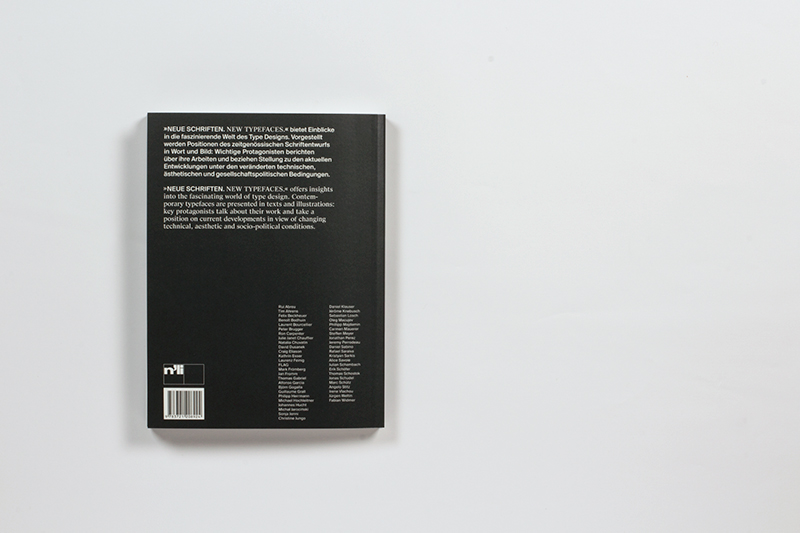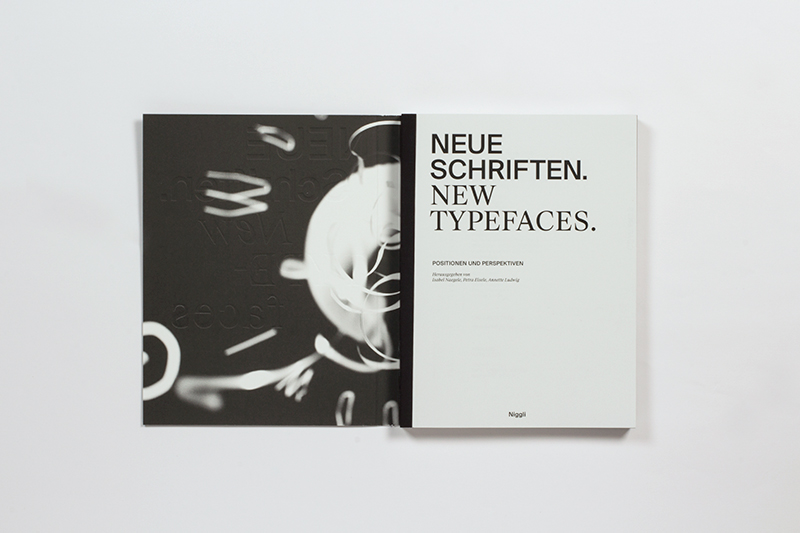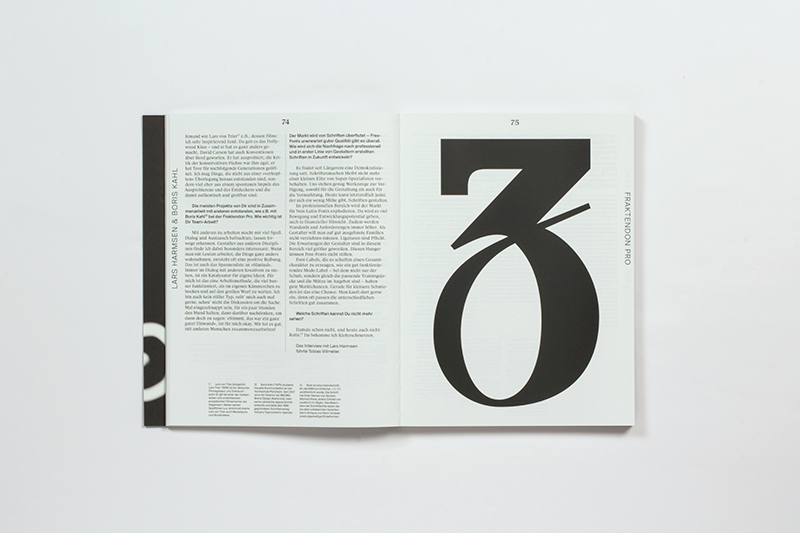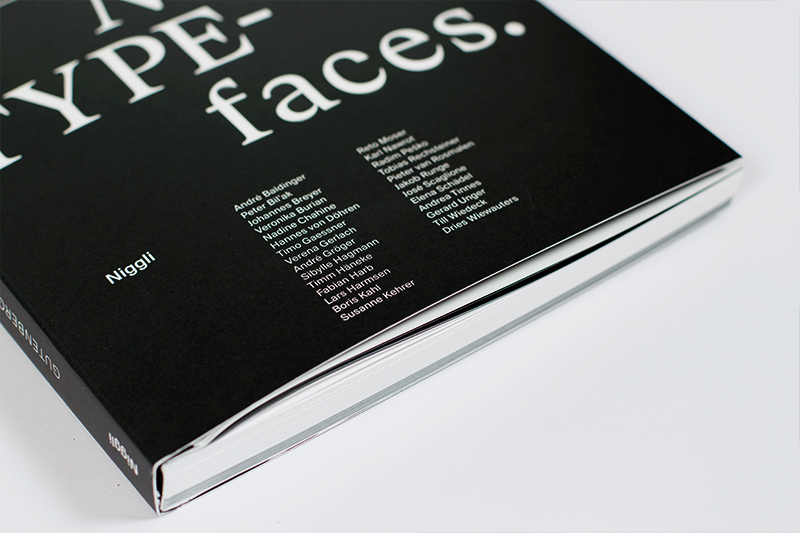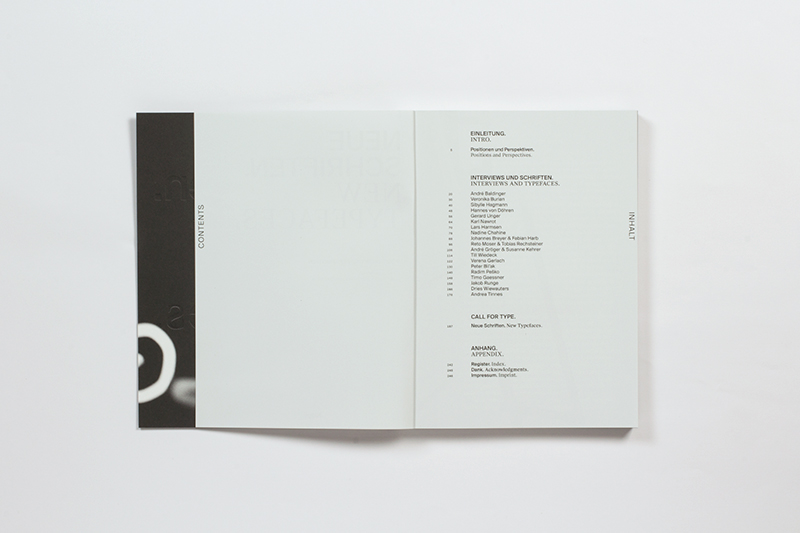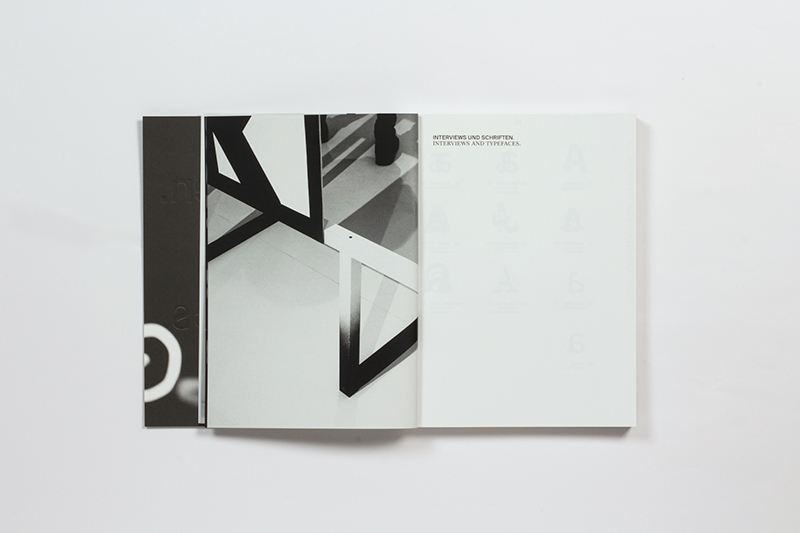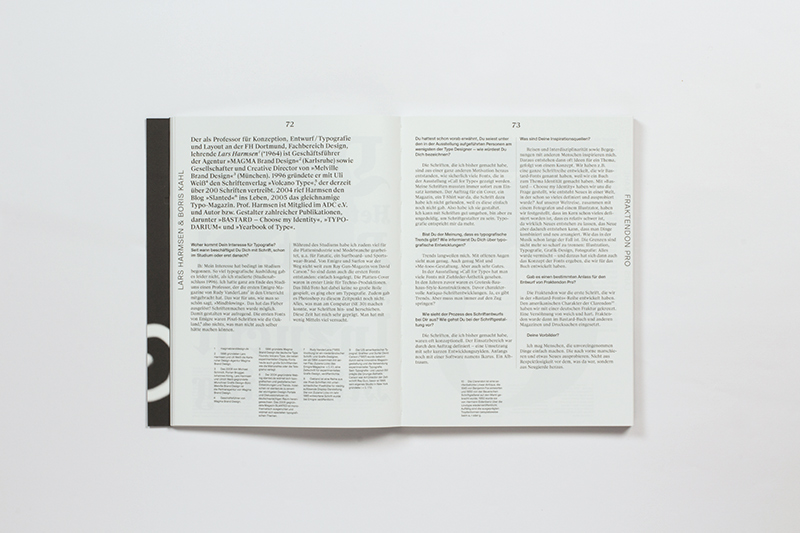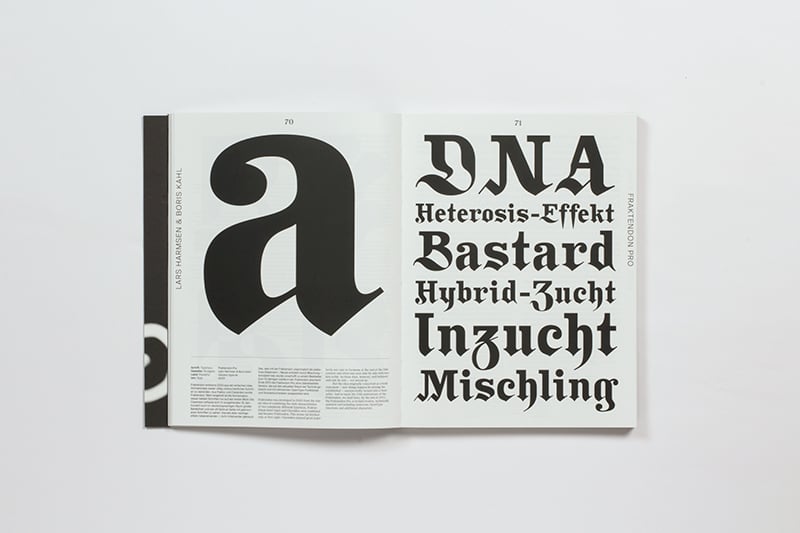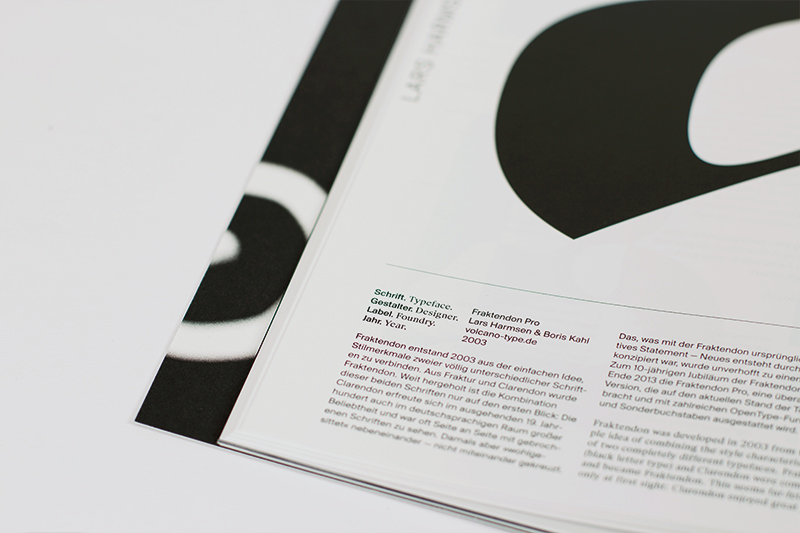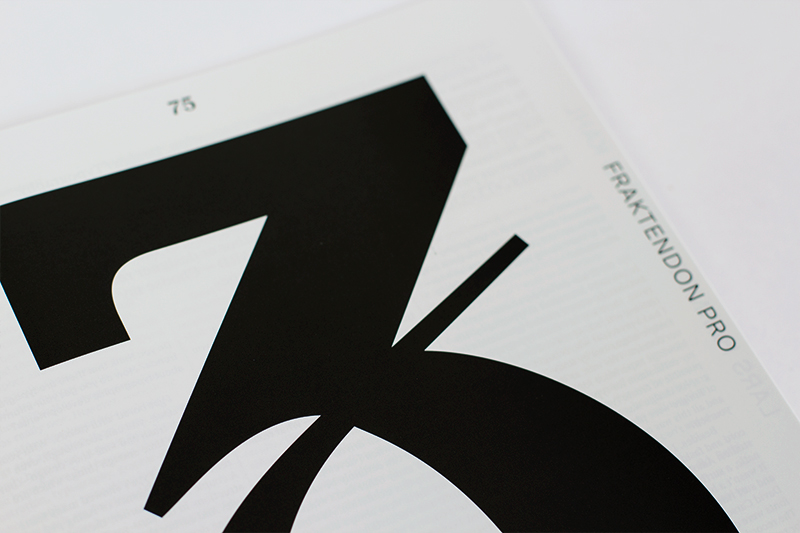
Neue Schriften. New Typefaces.
Im Niggli Verlag erschien vor kurzem das Buch »Neue Schriften. New Typefaces.« anlässlich der Ausstellung “Call for Type”, welche von Juni bis Ende Oktober im Gutenberg Museum Mainz statt fand. Auf 248 Seiten gibt die Publikation Einblicke in die komplexe Welt zeitgenössischer Schriftgestaltung.
Aus dem Pressetext: Neue Schriften. New Typefaces. bietet Einblicke in die faszinierende Welt des Type-Designs. Vorgestellt werden Positionen des zeitgenössischen Schriftentwurfs in Wort und Bild: Wichtige Protagonisten berichten über ihr Denken und Arbeiten, sodass aktuelle Entwicklungen unter den neuen technischen, ästhetischen und gesellschaftspolitischen Bedingungen nicht nur vorgestellt, sondern auch bewertet werden können. Wurden in den Siebzigerjahren jährlich noch wenige hundert Schriften veröffentlicht, können wir heute zwischen zehntausenden Fonts wählen – Tendenz steigend.
Dass sich aktuelles Type-Design dennoch keinesfalls in Beliebigkeit oder einem modischen Hype erschöpft, verdeutlicht diese Publikation: Aus dem reichen, internationalen Schriftkosmos präsentiert sie experimentelle Schriftentwürfe, die von einer spontanen Idee oder der Konzeption eines selbst gewählten Gestaltungsprojekts ausgehen; Display-Fonts mit wenigen Schnitten oder Leseschriften mit umfangreichen Schriftfamilien, die, oft über Jahre hinweg, mit leidenschaftlicher Ausdauer und einer unerschütterlichen Liebe zu den charakteristischen Details systematisch ausgebaut werden. In ihrer Gesamtheit dokumentiert die Publikation Neue Schriften. New Typefaces daher nicht nur die hohe Professionalität, sondern auch den ernsthaften Enthusiasmus, der Schriftgestalterinnen und -gestalter heute antreibt.
Neue Schriften. New Typefaces.
Herausgeber: Petra Eisele, Isabel Naegele, Annette Ludwig
Verlag: Niggli
Gestaltung: Jens-Peter Giesel, Yvonne Kümmel